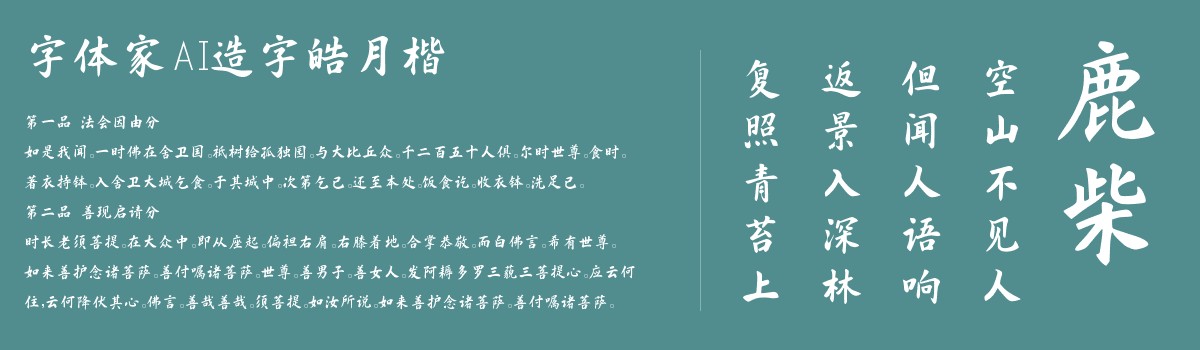
字体家AI造字皓月楷
字体家AI造字皓月楷是一款由字体家AI神笔造字生成的艺术字体,笔画圆润舒展,起收笔无尖锐棱角,如月光轻抚般柔和。横画微扬显灵动,竖画挺直如柱稳重心。撇捺由粗及细,末端轻盈似羽翼;点画饱满若凝露,位置精准。结构严谨端庄,各部比例协调,无刻意夸张。整体温润典雅,如书卷般沉静,兼具力量与柔美,清朗平和。适合用于一些广告标题、平面文案、海报标题、网页广告用字的编辑。